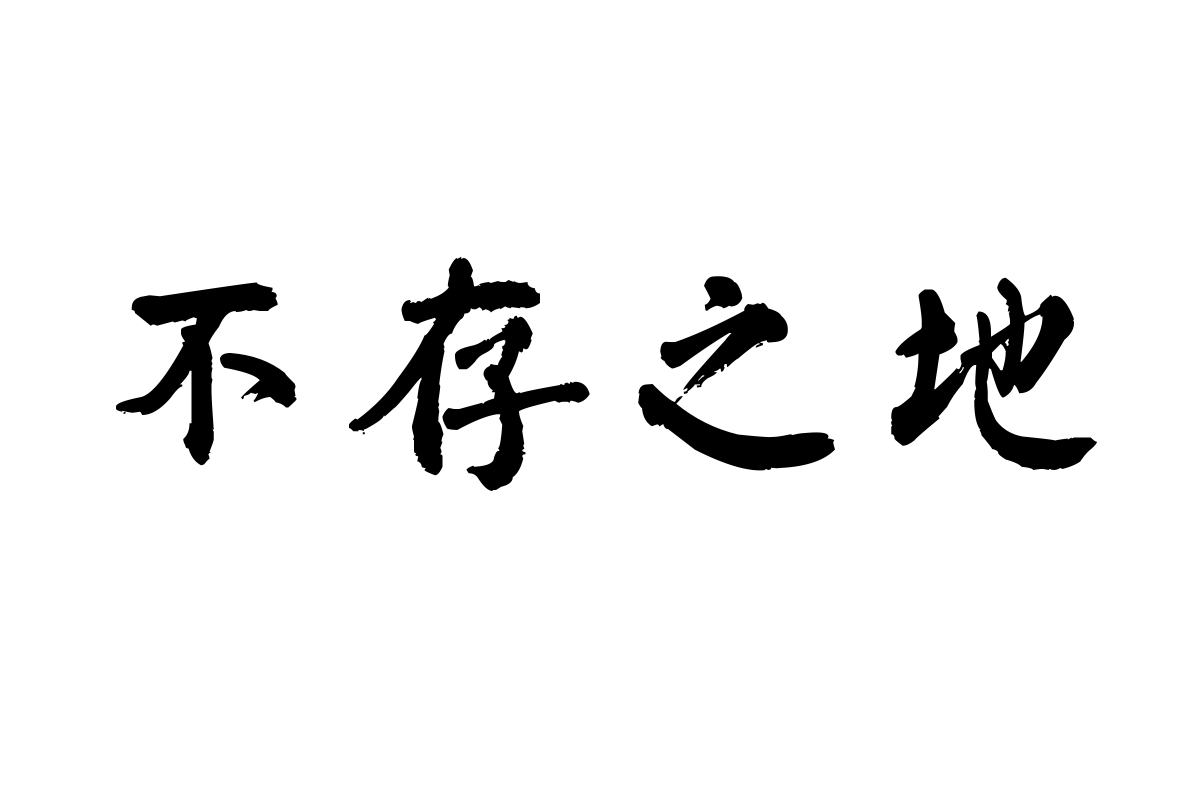
汉呈杨仁志榜书字体是一种具有独特风格的书法字体,以其流畅、自然和优雅的特点而闻名。这种字体的特点是笔画圆润,线条流畅,给人一种轻松愉悦的感觉。它的结构紧凑,字形规整,适合用于书写各种文本和艺术作品。
该字体的笔画粗细适中,既有力度又有弹性,使得书写起来既舒适又富有表现力。它的笔锋饱满,线条清晰,能够很好地表现出文字的美感和节奏感。此外,汉呈杨仁志榜书字体还具有一定的装饰性,可以通过不同的笔触和技巧来创造出丰富的视觉效果。
总的来说,汉呈杨仁志榜书字体是一种非常适合于书写中文的字体,它能够展现出中文的独特韵味和艺术魅力。无论你是从事写作、设计还是其他与文字相关的工作,都可以尝试使用这种字体来表达自己的创意和情感。